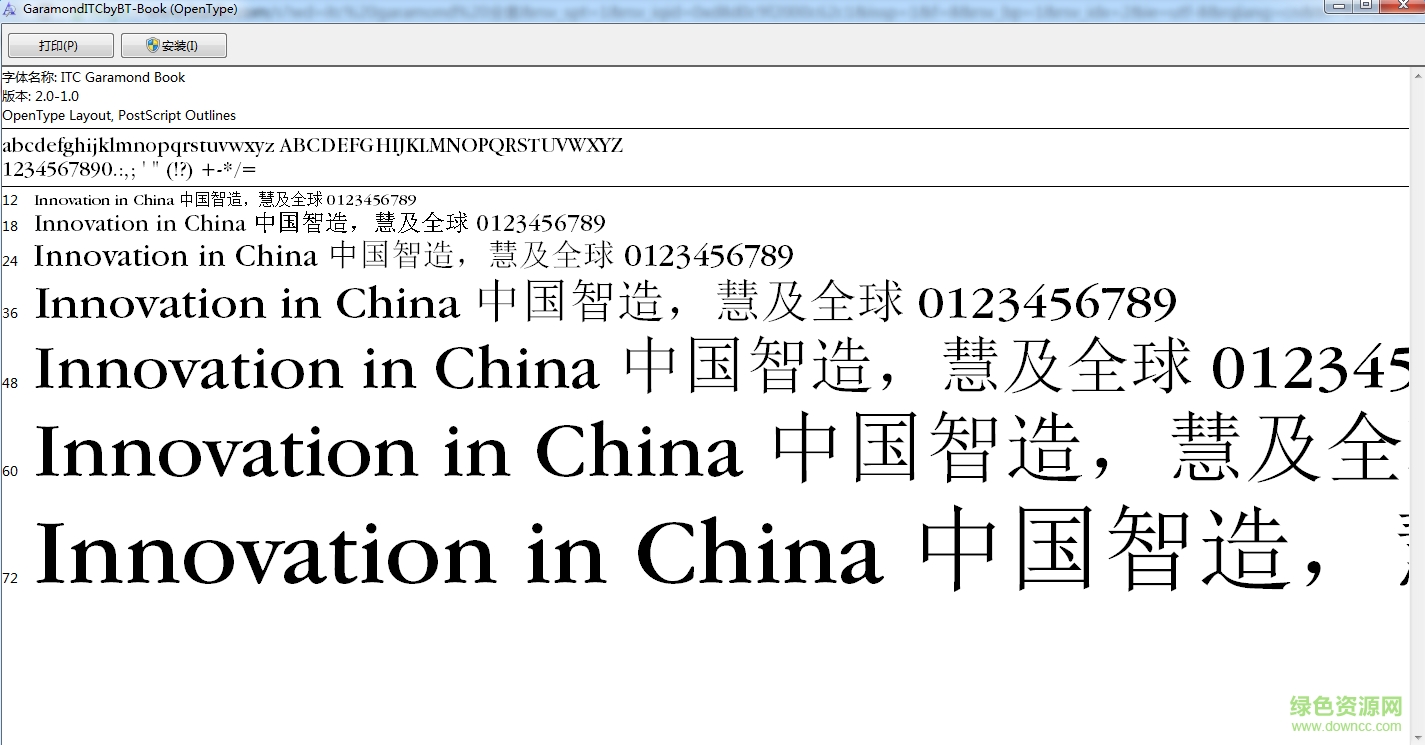
itc garamond字體可以說(shuō)是襯線字體的典范了,字體變化得宜,秀麗悅目,閱讀性強(qiáng),適合用來(lái)作大段文字排版,喜歡就來(lái)綠色資源網(wǎng)下載收藏吧!
Garamond是一類西文襯線字體的總稱,也是舊襯線體的代表字體。Garamond的字型有著流動(dòng)性和一致性,其最富特征的是小寫(xiě)字母a的小鉤和字母e的小孔。高字母和頂端襯線有長(zhǎng)斜面。
serif,意思是在字的筆畫(huà)開(kāi)始、結(jié)束的地方有額外的裝飾,而且筆畫(huà)的粗細(xì)會(huì)有所不同。serif字體容易識(shí)別,它強(qiáng)調(diào)了每個(gè)字母筆畫(huà)的開(kāi)始和結(jié)束,因此易讀性比較高,中文字體中的宋體就是一種最標(biāo)準(zhǔn)的serif字體,襯線的特征非常明顯。字形結(jié)構(gòu)也和手寫(xiě)的楷書(shū)一致。因此宋體一直被做為最適合的正文字體之一。